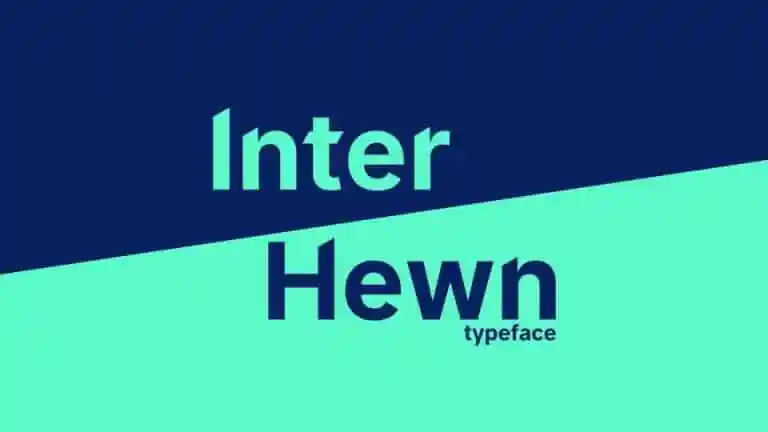
Inter Hewn Sans Serif Font – Fonte Grátis
Inter Hewn Sans Serif Font
Introduzimos a Inter Hewn Sans Serif Font, uma tipografia sans serif ideal tanto para uso impresso quanto digital. Este tipo de letra traz uma estética única e elegante, destacando os elementos básicos dos textos: linhas e ângulos agudos. A Inter Hewn é perfeitamente compatível com outras famílias como Helvetica, San Francisco ou Inter. Suas formas simples e modernas permitem que você destaque o texto em projetos de protótipo iOS ou web, dando-lhe um visual chamativo e atraente sem sacrificar a legibilidade. Uma escolha valiosa para qualquer projeto que valorize uma tipografia clean e contemporânea.